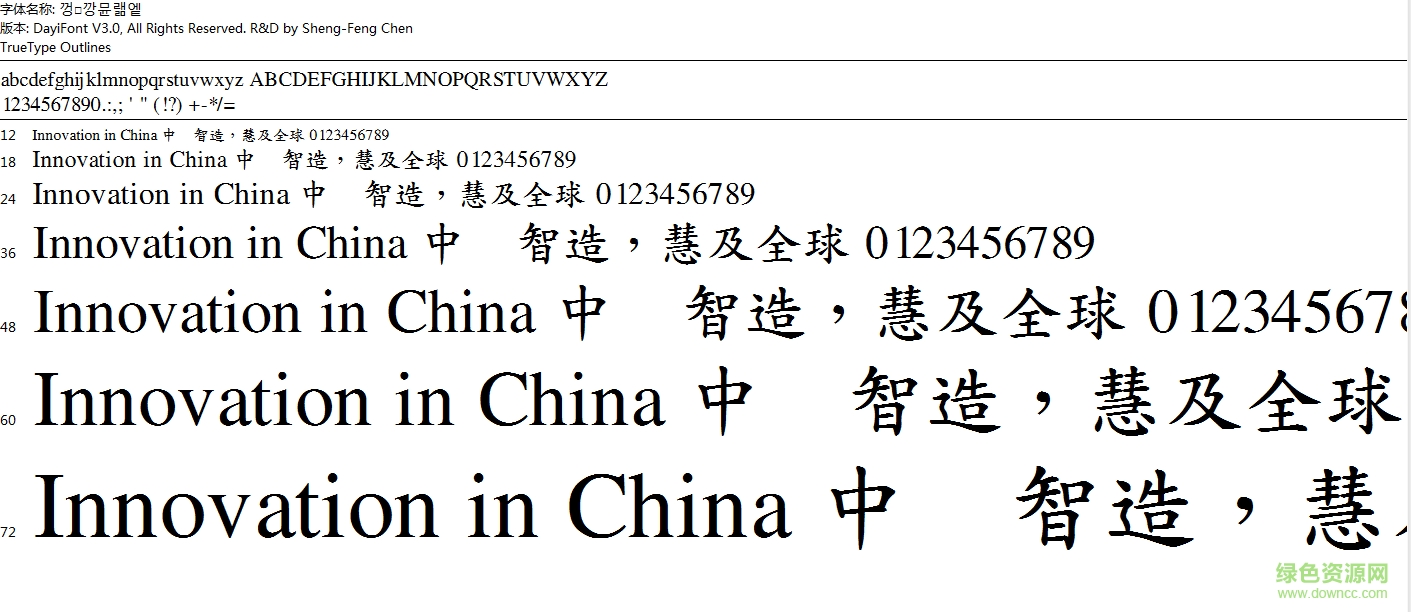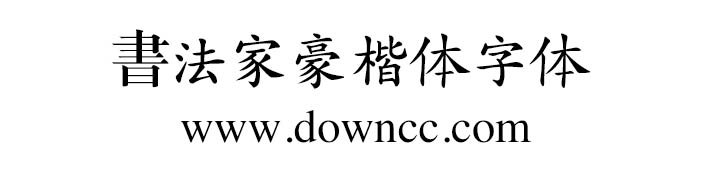
軟件介紹 軟件標簽: 書法家字體 字體 書法家豪楷體是專門為喜歡優(yōu)美字體的朋友們準備的,該字體頗有美感,現已被應用于中國大陸各個領域。喜歡就來綠色資源網下載吧!書法家豪楷體介紹書法家豪楷體具有字體獨有的個性,書寫方方正正,給人一種獨有的美感,是許多地方都可以使用的字體。書法家豪楷體安裝說明1、點擊打開書法家豪楷體(繁)字體,直接選擇安裝即可。2、將字體復制到C:\Windows\Fonts文件夾即可完成安裝。注意事項本站所有字體資源僅供個人學習與參考,如需商業(yè)使用請到相關官網授權。 軟件截圖 上一張下一張(1 / 1) 安裝詳細截圖 猜你喜歡 書法字體 楷書字體 書法字體 書法字體有哪些?主要包括了硬筆書法字體、英文書法字體和毛筆書法字體三大類,綠色資源網提供了多款好看的常用各種書法字體文件打包下載,如:李旭科書法字體、啟功書法字體等,趕快下載體驗吧! 查看更多>> 蔡云漢隸書書法字體ttf 2.61M/中文/10.0/下載 黃庭堅字體 2.39M/中文/6.6/下載 李旭科書法v1.4-中 3.59M/中文/7.7/下載 金梅書法豆豆 2.03M/中文/10.0/下載 金梅新海報書法 2.24M/中文/10.0/下載 劉夢吟書法行楷字體 3.66M/中文/10.0/下載 楷書字體 楷書字體是綠色資源網小編專為大家收集的一類非常流行而且好用的楷書字體,它包括了各種形式的楷書??瑫步姓?、真書、正書。從程邈創(chuàng)立的隸書逐漸演變而來,更趨簡化,橫平豎直,筆勢雄奇,姿態(tài)橫生,可應用于繪畫設計、藝術創(chuàng)作、平面廣告、印刷包裝、電視廣告等等各行各業(yè)。也是現在很多行業(yè)必用的一類字體,小編收集的這一類楷書字體希望能更好的幫助大家收集和使用楷書字體。 查看更多>> 楷體國標字體官方版 2.45M/中文/7.1/下載 漢儀閃耀楷書字體 1.77M/中文/0.0/下載 華為漢儀錦時楷書 2.92M/中文/5.0/下載 楷書字典手機版 4.46M/中文/5.0/v2.0 安卓版下載 經典楷體繁體 3.96M/中文/5.0/下載 楷書繁體字體包 9.76M/中文/8.0/下載 其他版本下載 標題 大小 更新日期 下載 下載地址 電腦版 書法家豪楷體字體 點擊報錯 軟件無法下載或下載后無法使用,請點擊報錯,謝謝! 關閉報錯反饋 請描述您所遇到的錯誤,我們將盡快予以修正,謝謝! *必填項,請輸入內容 本類最新 datm9 datx2 datk8 dath9 datk6 書法家特圓體字體 相關文章 Photoshop字體安裝使用方法和技巧 如何解決“無法新增字體”問題 Win 7系統(tǒng)安裝字體方法 網頁字體大小設置方法 怎么改網頁字體大小 在Linux系統(tǒng)中安裝字體的幾種方法 windows7字體顯示問題:打開某些程序的時候顯示的是亂碼 用戶評論 熱門評論 最新評論 發(fā)表評論 查看所有評論(0) 昵稱: 請不要評論無意義或臟話,我們所有評論會有人工審核. 字數: 0/500 (您的評論需要經過審核才能顯示)